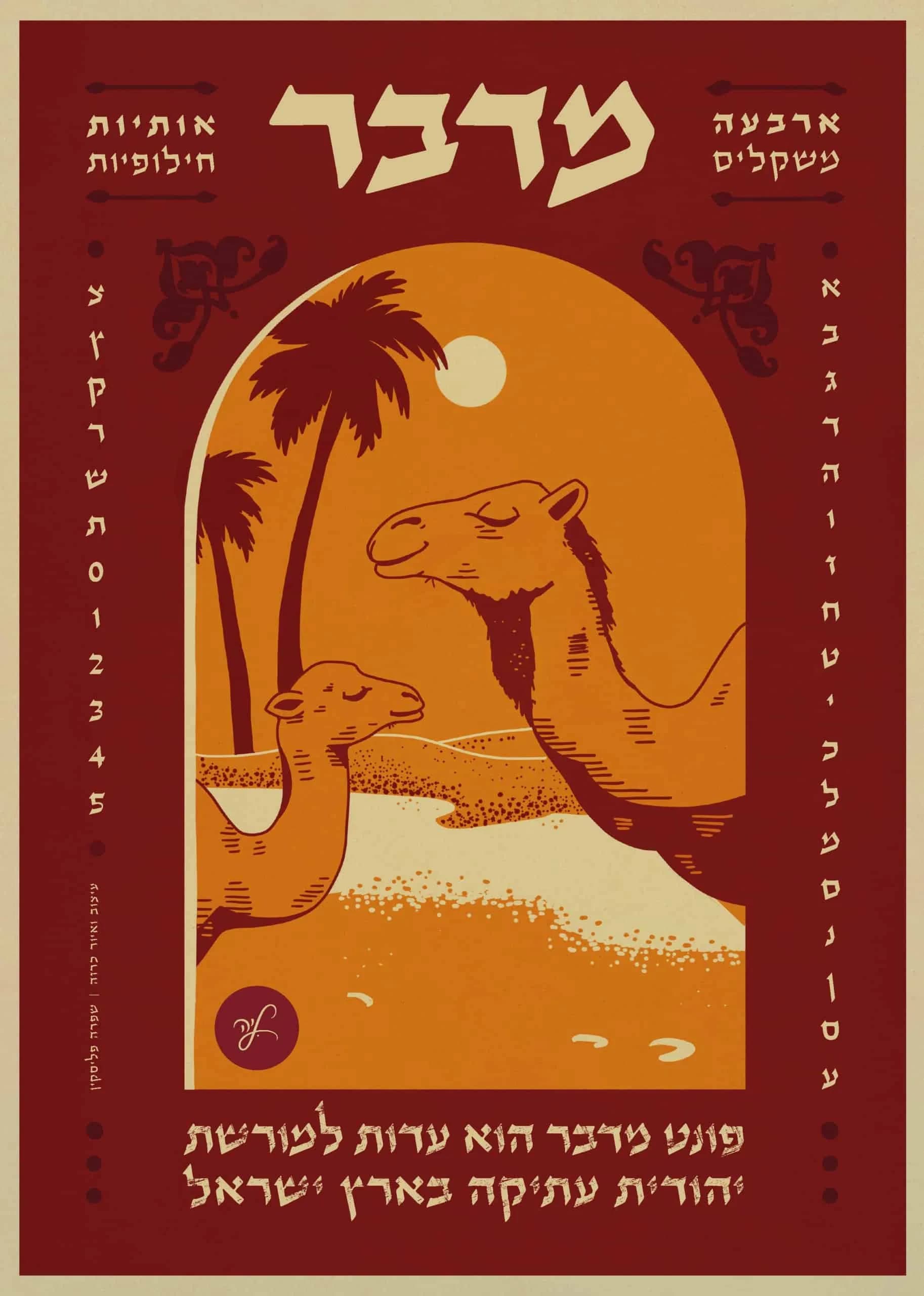
מדבר פרשנות קליגרפית לכתבים העתיקים שנמצאו על המגילות של קומראן. ״מדבר״ אינו רק גופן, זוהי עדות למורשת המתמשכת של ציוויליזציה יהודית עתיקה בארץ ישראל. הקווים הזורמים והצורות האלגנטיות מגלמות את המהות של הטקסטים ההיסטוריים הללו, ותורמים לאווירה של מיסטיקה ומסורת.